Mỗi độ thu về, khi cái se lạnh khẽ chạm ngõ và hương hoa sữa len lỏi qua từng con phố nhỏ, cũng là lúc ánh trăng rằm tháng Tám chuẩn bị thắp sáng bầu trời đêm. Tết Trung Thu – Tết Đoàn viên – không chỉ là một trong những lễ hội cổ truyền thiêng liêng nhất của người Việt, mà còn là một “mùa vụ” sáng tạo đầy rực rỡ của giới thiết kế đồ họa. Trong nhịp sống hiện đại, Trung Thu không chỉ quẩn quanh bên mâm cỗ với bánh nướng, bánh dẻo hay chiếc đèn ông sao, mà nó đã trở thành một không gian nghệ thuật, nơi các thương hiệu kể câu chuyện của mình qua từng ấn phẩm truyền thông, bao bì sản phẩm và những sự kiện hoành tráng.
Đánh Thức Xúc Cảm Mùa Trăng 2026: Trọn Bộ Font Việt Hóa Trung Thu Khơi Nguồn Sáng Tạo Bất Tận
Để biến những ý tưởng vô hình thành những tác phẩm thị giác chạm đến trái tim người xem, typography (nghệ thuật chữ) chính là chiếc chìa khóa vạn năng. Một thông điệp dù ý nghĩa đến đâu cũng sẽ trở nên nhạt nhòa nếu bị đặt sai phông chữ. Hiểu thấu những trăn trở và áp lực của các Designer, Agency trong mùa cao điểm, Fontmienphi.com tự hào mang đến siêu dự án: Bộ Sưu Tập Font Việt Hóa Chủ Đề Trung Thu 2026. Đây là kết tinh của sự tỉ mỉ, thấu hiểu văn hóa và tư duy thẩm mỹ hiện đại, sẵn sàng đồng hành cùng bạn kiến tạo nên những tuyệt tác thiết kế.
Tầm Quan Trọng Của Typography Trong Thiết Kế Trung Thu
Thiết kế mùa Trung Thu là một bài toán khó nhưng cũng đầy thú vị. Nó đòi hỏi người thiết kế phải tìm ra điểm cân bằng hoàn hảo giữa việc gìn giữ những giá trị văn hóa truyền thống và việc thổi vào đó hơi thở của thời đại mới.
Khi khách hàng nhìn vào một hộp bánh Trung Thu cao cấp, thứ đầu tiên thu hút họ chưa chắc đã là hình ảnh minh họa, mà chính là những dòng chữ tên thương hiệu, tên sản phẩm được nắn nót tỉ mỉ. Phông chữ thư pháp gợi nhớ về sự hoài cổ, nét chữ cứng cáp, dứt khoát mang đến vẻ sang trọng, hoàng gia, trong khi những nét chữ tròn trịa, uốn lượn lại đưa ta về với miền ký ức tuổi thơ hồn nhiên.
Sự tinh tế của một bộ font việt hóa chất lượng nằm ở chỗ các dấu câu (diacritics) tiếng Việt được xử lý một cách mượt mà. Không có gì phá hỏng một bản thiết kế nhanh hơn việc một chữ “ẵ” hay “ệ” bị xô lệch khoảng cách (kerning) hoặc bị lỗi phông chữ (tofu error). Thấu hiểu điều này, toàn bộ các font chữ tại Fontmienphi.com đều được các chuyên gia typography tinh chỉnh đến từng pixel, đảm bảo hiển thị hoàn hảo trên mọi nền tảng, từ in ấn khổ lớn đến màn hình thiết bị di động.
Giải Mã Sức Hút Của Top 10 Font Việt Hóa Trung Thu 2026
Dưới đây là một hành trình khám phá chi tiết 10 “viên ngọc quý” trong bộ sưu tập năm nay. Mỗi phông chữ mang một linh hồn riêng, một sắc thái riêng, chờ đợi bạn đánh thức và đưa vào những tác phẩm vĩ đại của mình.
1. Font Việt Hóa LNTH DeBorstel Brush – Nét Cọ Phóng Khoáng, Rực Rỡ Đêm Hội
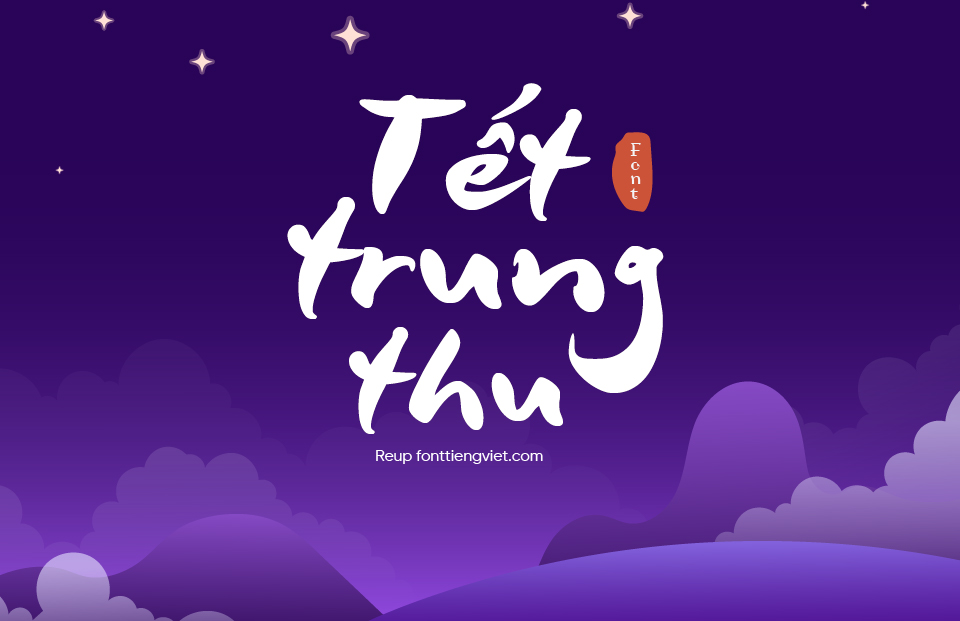
Khi âm vang của tiếng trống lân rộn rã vang lên, bạn cần một phông chữ có thể bắt nhịp được sự sôi động đó. LNTH DeBorstel Brush chính là câu trả lời. Được thiết kế mô phỏng theo những nét cọ vuốt dứt khoát, phông chữ này mang lại cảm giác tràn đầy năng lượng và sự tự do.
Ứng dụng: Tuyệt vời cho các tiêu đề (Heading) trên poster sự kiện đêm rằm, banner quảng cáo các chương trình khuyến mãi mùa Trung Thu. Nét cọ mạnh mẽ của nó khi kết hợp với hiệu ứng chữ vàng gold bóng bẩy trên nền đỏ thẫm sẽ tạo ra sức hút thị giác không thể chối từ.
2. Font Việt hóa LNTH Henri Modeste – Sự Thanh Lịch Tôn Cấp Bao Bì
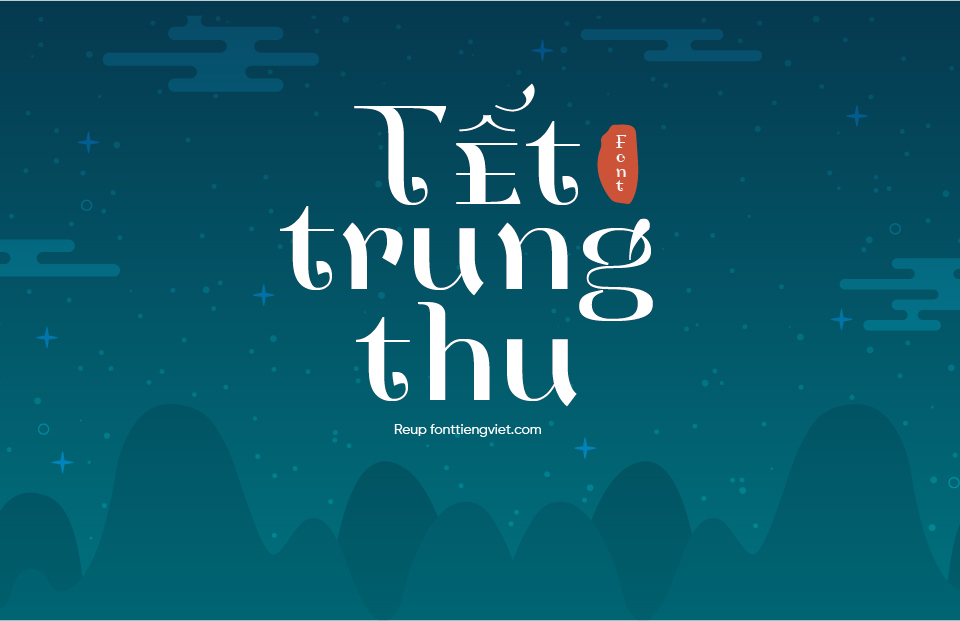
Trái ngược với sự ồn ào, LNTH Henri Modeste mang đến một khoảng lặng tinh tế và đầy tính hàn lâm. Đây là một phông chữ Serif (có chân) với tỷ lệ vàng chuẩn mực, những nét thanh nét đậm được tính toán kỹ lưỡng để tạo ra sự sang trọng tối đa.
Ứng dụng: Đây là “chân ái” cho các thiết kế bao bì bánh Trung Thu thuộc phân khúc cao cấp (premium). Phông chữ này giúp tên thương hiệu của bạn toát lên sự đài các, đẳng cấp, cực kỳ phù hợp khi kết hợp cùng các kỹ thuật in ấn như ép kim (Foil Stamping) hay thúc nổi (Embossing) trên nền giấy mỹ thuật.
3. Font Việt Hóa LNTH Pincoya Black – Cực Chất, Cực Quyền Lực
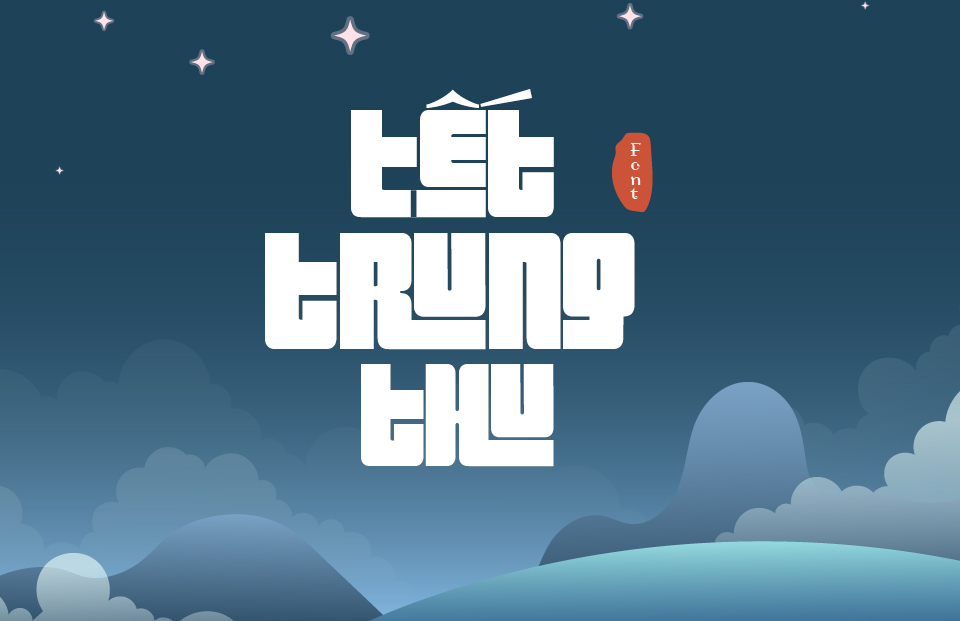
Đôi khi, để thông điệp truyền thông ghi dấu ấn ngay lập tức trong 3 giây lướt mạng xã hội, bạn cần một sự “nặng ký” thực sự. LNTH Pincoya Black sở hữu trọng lượng chữ (font weight) cực kỳ dày dặn, các ký tự đứng sát nhau tạo nên một khối vững chắc.
Ứng dụng: Phù hợp làm Key Visual cho các chiến dịch flash sale mùa Trung Thu, hoặc những ấn phẩm thiết kế hướng tới tệp khách hàng Gen Z năng động. Phông chữ này sẽ thực sự “bùng nổ” nếu bạn áp dụng thêm các hiệu ứng 3D hoặc viền neon phát sáng.
4. Font Việt Hóa LNTH Peter Obscure – Lạc Bước Vào Miền Cổ Tích
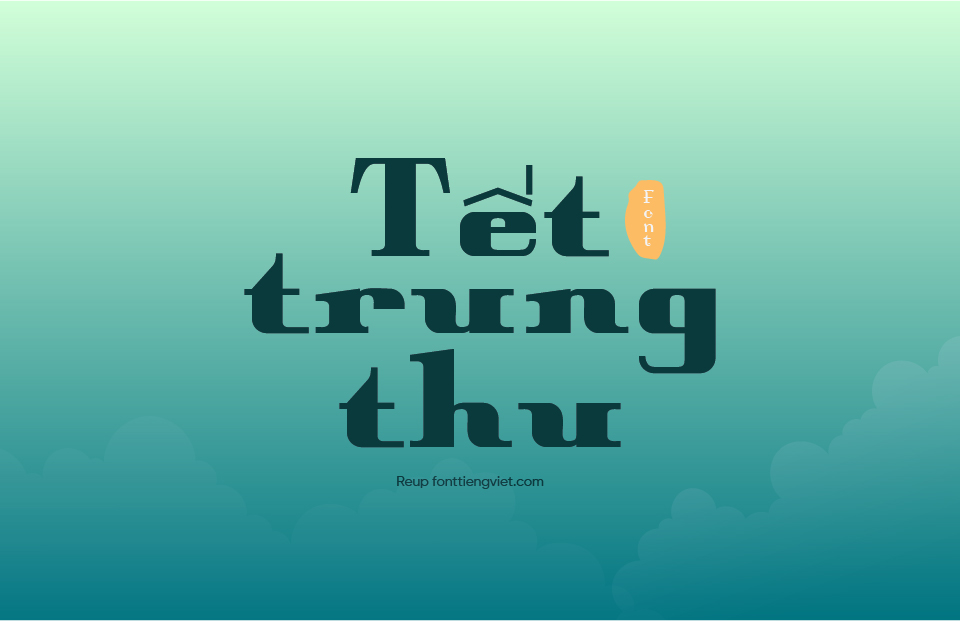
Trung Thu là Tết của thiếu nhi, là đêm của những câu chuyện cổ tích về chú Cuội ngồi gốc cây đa, về chị Hằng Nga xinh đẹp và Thỏ Ngọc trên cung trăng. LNTH Peter Obscure với những đường nét cách điệu mềm mại, uốn lượn có chủ ý, mang lại một cảm giác huyền bí, nhiệm màu và đầy tính tự sự.
Ứng dụng: Rất lý tưởng để thiết kế typography cho các quyển truyện tranh, sách ảnh thiếu nhi chủ đề Trung Thu, hoặc dùng để trích dẫn những câu thơ, lời chúc ý nghĩa trên các tấm thiệp đính kèm hộp quà tặng.
5. Font Việt Hóa LNTH Nee – Ngọt Ngào Ký Ức Tuổi Thơ
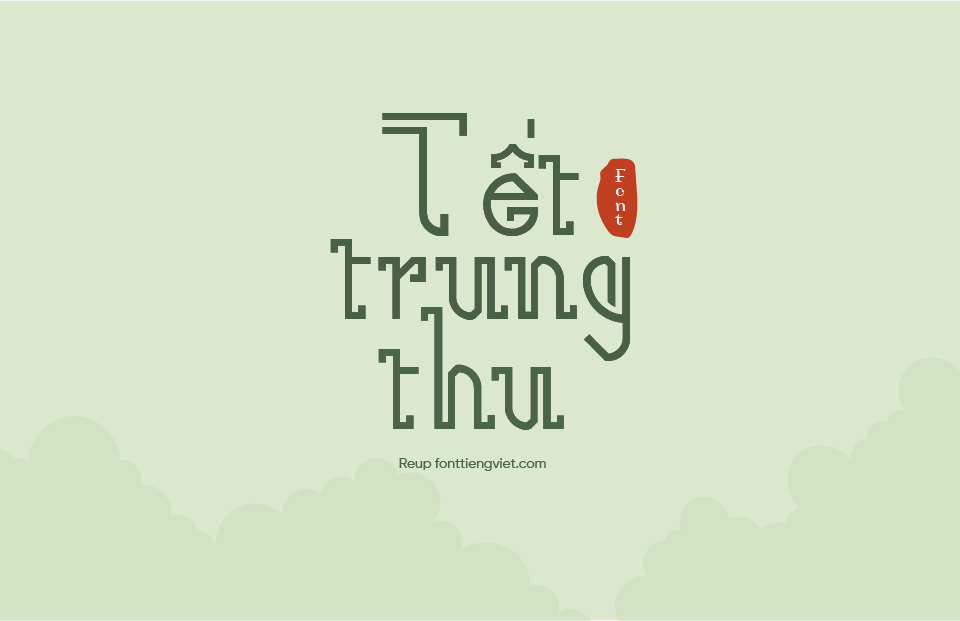
Không cầu kỳ, không hoa mỹ, sức mạnh của LNTH Nee nằm ở sự gần gũi, đáng yêu và trong trẻo. Dáng chữ nghiêng nhẹ nhàng như những nét chữ viết tay nắn nót của tuổi học trò, gọi về những ký ức rước đèn ông sao khắp xóm nhỏ.
-
Ứng dụng: Phông chữ này sinh ra để dành cho các thiết kế mang concept gia đình, tình thân. Từ các bài đăng tương tác (minigame) trên fanpage, cho đến thiết kế bao bì cho các sản phẩm bánh handmade, bánh hình thú đáng yêu dành riêng cho các bé.
6. Font Việt Hóa LNTH Hieroglyphic – Đột Phá Bằng Hơi Hướng Cổ Kính
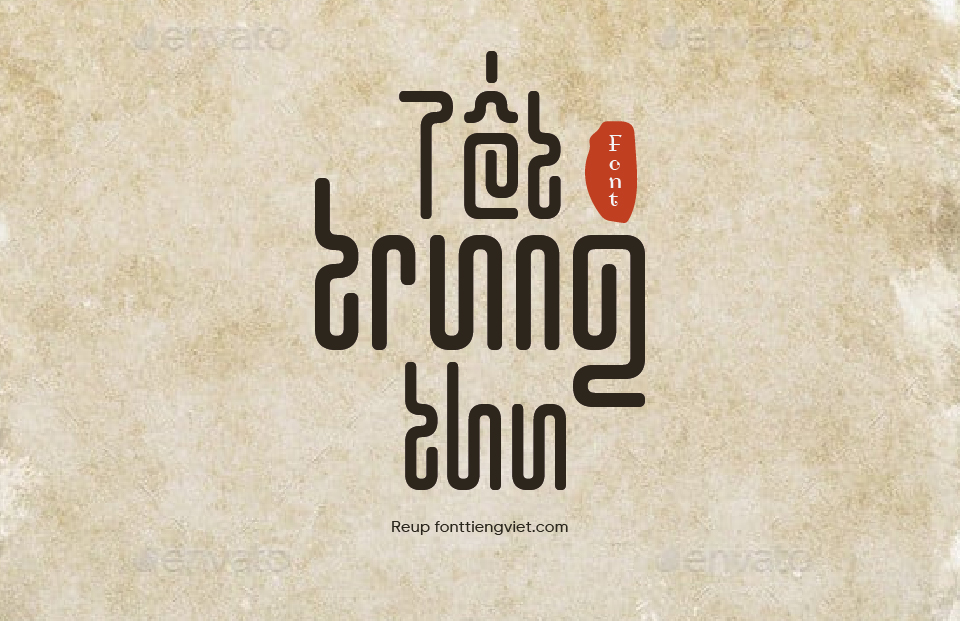
Bạn đã quá chán với những phông chữ thư pháp an toàn? LNTH Hieroglyphic mang đến một làn gió mới bằng việc giao thoa giữa nét khắc đá cổ xưa và tư duy hình khối hiện đại. Nó góc cạnh, gai góc nhưng lại vô cùng hài hòa khi được sắp xếp bố cục.
-
Ứng dụng: Lựa chọn hoàn hảo cho các thiết kế mang hơi hướng Cổ Phong Á Đông, các dự án nghệ thuật đương đại, hoặc thiết kế hộp trà cao cấp. Phông chữ này mang lại một sự uy nghi, trầm mặc, giúp tác phẩm của bạn nổi bật giữa đám đông.
7. Font Việt Hóa LNTH Daybreaker – Mảnh Ghép Của Ánh Bình Minh
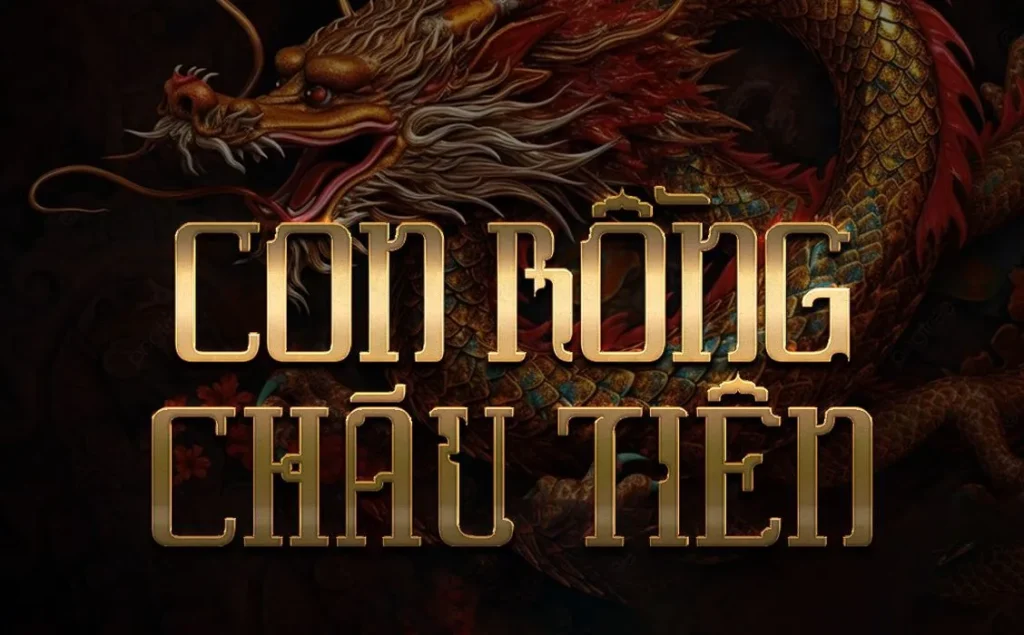
Đại diện cho sự năng động và bứt phá, LNTH Daybreaker là một phông chữ Brush (cọ) mang tính hiện đại cao. Nó không quá truyền thống nhưng lại giữ được sự mềm mại cần thiết của một lễ hội Á Đông.
-
Ứng dụng: Cực kỳ phù hợp cho các thiết kế thương mại điện tử, các banner chạy quảng cáo Shopee, Tiktok Shop mùa lễ hội. Khả năng hiển thị sắc nét giúp thông điệp của bạn luôn nổi bật trên màn hình di động.
8. Font Việt Hóa LNTH Guttenberg MF – Sợi Dây Liên Kết Về Mùa Thu Xưa
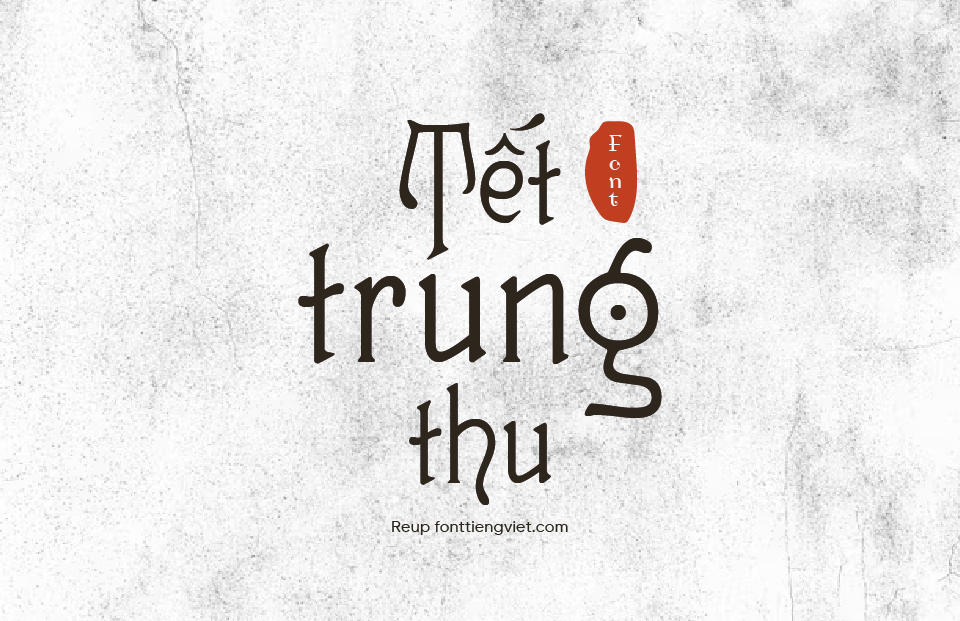
Vintage và Retro chưa bao giờ lỗi thời trong thiết kế Trung Thu. LNTH Guttenberg MF tái hiện lại kỹ thuật in chữ chì (letterpress) của thế kỷ trước với những đường nét hơi sần sùi, thô mộc.
-
Ứng dụng: Là linh hồn của các thiết kế theo concept “Trung Thu Xưa”. Hãy thử kết hợp phông chữ này với tông màu giấy kraft, đỏ gạch và xanh rêu, bạn sẽ tạo ra những tấm poster hay bao bì mang đậm tính nghệ thuật hoài niệm, chạm đến những cảm xúc sâu kín nhất của những người trưởng thành xa quê.
9. Font Việt Hóa 1FTV Cat Franken Deutsch – Sự Ma Mị Khó Cưỡng
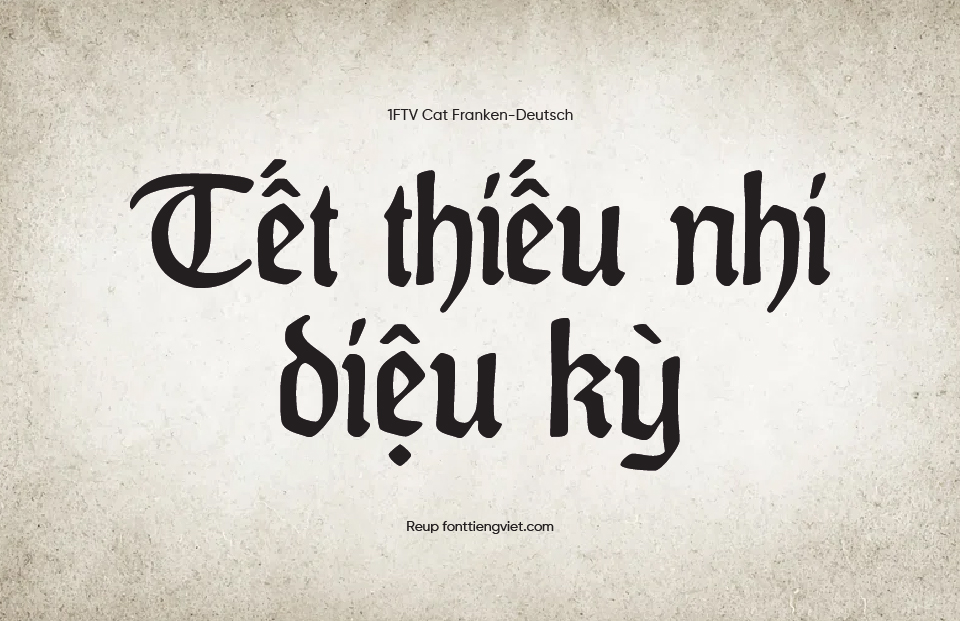
Sự xuất hiện của một phông chữ mang âm hưởng Gothic (Blackletter) trong chủ đề Trung Thu có vẻ kỳ lạ, nhưng đó chính là sự phá cách mà thời đại mới cần. 1FTV Cat Franken Deutsch mang đến một vẻ đẹp góc cạnh, ma mị và cực kỳ cuốn hút.
-
Ứng dụng: Sinh ra để dành cho những dự án thiết kế “độc bản”, các sự kiện đêm rằm kết hợp âm nhạc điện tử, hoặc các thương hiệu muốn định hình phong cách cá tính, nổi loạn và vượt qua mọi giới hạn an toàn.
10. Combo Font Trung Thu – Font Việt Hóa Trung Thu 2025: Di Sản Kế Thừa Trọn Vẹn
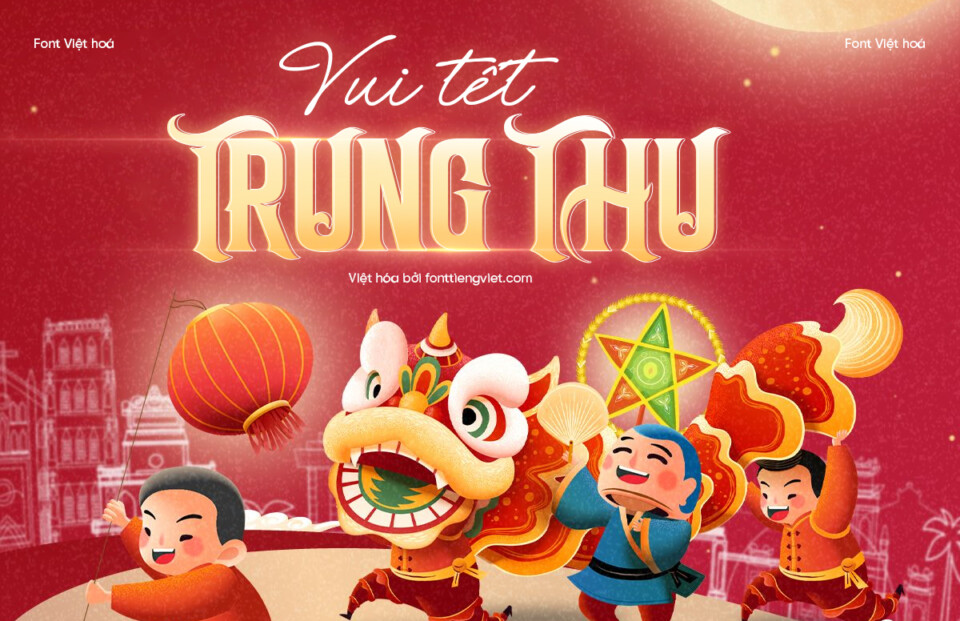
Dù là xu hướng của năm 2026, nhưng giá trị của nghệ thuật là vĩnh cửu. Combo 1 quy tụ những phông chữ kinh điển nhất đã làm mưa làm gió trong mùa trăng năm trước. Đây là một bộ tài nguyên vô giá, một giải pháp “All-in-One” giúp các designer có sẵn một kho vũ khí đa dạng phong cách, tối ưu hóa workflow và xử lý mọi yêu cầu khắt khe từ phía khách hàng chỉ trong chớp mắt.
Tải Ngay Combo – Font Việt Hóa Trung Thu 2025: Trọn Bộ Giải Pháp Typography Mùa Trăng
Bí Quyết Kết Hợp Font Chữ (Font Pairing) Nâng Tầm Thiết Kế
Sở hữu font chữ đẹp mới chỉ là một nửa chặng đường. Để một ấn phẩm thực sự “biết nói”, bạn cần nắm vững nguyên tắc kết hợp phông chữ:
-
Sự tương phản (Contrast): Luôn kết hợp một font mang tính trang trí cao (Display/Brush/Script) như LNTH DeBorstel Brush ở phần Tiêu đề, đi kèm với một font không chân (Sans-serif) thanh mảnh, tối giản ở phần nội dung mô tả để đảm bảo tính dễ đọc.
-
Sự phân cấp (Hierarchy): Sử dụng các kích thước và trọng lượng chữ khác nhau để dẫn dắt ánh nhìn của người xem từ thông điệp chính đến thông tin chi tiết.
-
Sự hòa hợp với màu sắc: Phông chữ cổ điển như LNTH Guttenberg MF sẽ đẹp nhất khi đi với các gam màu trầm ấm (đỏ đô, vàng đất). Ngược lại, phông chữ hiện đại như LNTH Daybreaker có thể kết hợp với các gam màu neon nổi bật.
Bứt Phá Giới Hạn Với Đặc Quyền VIP Từ Fontmienphi.com
Bạn đã sẵn sàng để biến những ý tưởng thiết kế Trung Thu 2026 của mình thành hiện thực? Tại Fontmienphi.com, chúng tôi cung cấp hàng ngàn phông chữ việt hóa chất lượng cao, chia sẻ hoàn toàn miễn phí để cộng đồng Designer Việt Nam cùng nhau phát triển.
Thế nhưng, nếu bạn là một nhà thiết kế chuyên nghiệp, một Agency quảng cáo hay Chủ doanh nghiệp đang tìm kiếm sự độc tôn và tối ưu hiệu suất, thì Gói VIP Fontmienphi.com chính là sự đầu tư xứng đáng nhất của bạn trong năm nay.
Tại sao bạn cần nâng cấp Gói VIP ngay hôm nay?
-
Tốc độ không giới hạn & Không quảng cáo: Thời gian là vàng bạc, nhất là trong mùa chạy Deadline. Gói VIP giúp bạn tải nguyên bộ sưu tập chỉ với một cú click, bỏ qua hoàn toàn các bước chờ đợi rút gọn link hay quảng cáo phiền phức.
-
Truy cập kho Font Bản Quyền Thương Mại: An tâm tuyệt đối khi sử dụng font cho các chiến dịch quảng cáo lớn của doanh nghiệp mà không phải lo lắng về rủi ro vi phạm bản quyền (Copyright).
-
Hỗ trợ kỹ thuật 24/7: Giải quyết ngay lập tức các vấn đề về hiển thị, lỗi cài đặt trên các phần mềm như Adobe Illustrator, Photoshop hay Premiere.
Dịch Vụ Việt Hóa Font & Thiết Kế Font Độc Quyền (Custom Font Services)
Bạn vô tình lướt thấy một phông chữ tuyệt đẹp trên Behance hay Pinterest nhưng nó lại chưa hỗ trợ tiếng Việt? Thương hiệu của bạn muốn sở hữu một bộ font chữ nhận diện (Brand Typography) độc quyền, không đụng hàng với bất kỳ ai trên thị trường?
Đừng để rào cản ngôn ngữ cản bước sự sáng tạo! Fontmienphi.com tự hào cung cấp Dịch vụ Liên hệ mua font và Việt hóa theo yêu cầu. Đội ngũ chuyên gia typography của chúng tôi sẽ tiến hành:
-
Phân tích cấu trúc, thiết kế thêm bộ dấu tiếng Việt (dấu ngã, dấu hỏi, dấu nặng…) đồng bộ 100% với phong cách gốc.
-
Xử lý Kerning thủ công tỉ mỉ cho từng cặp ký tự tiếng Việt, đảm bảo văn bản hiển thị hoàn hảo, không bị đứt gãy nét.